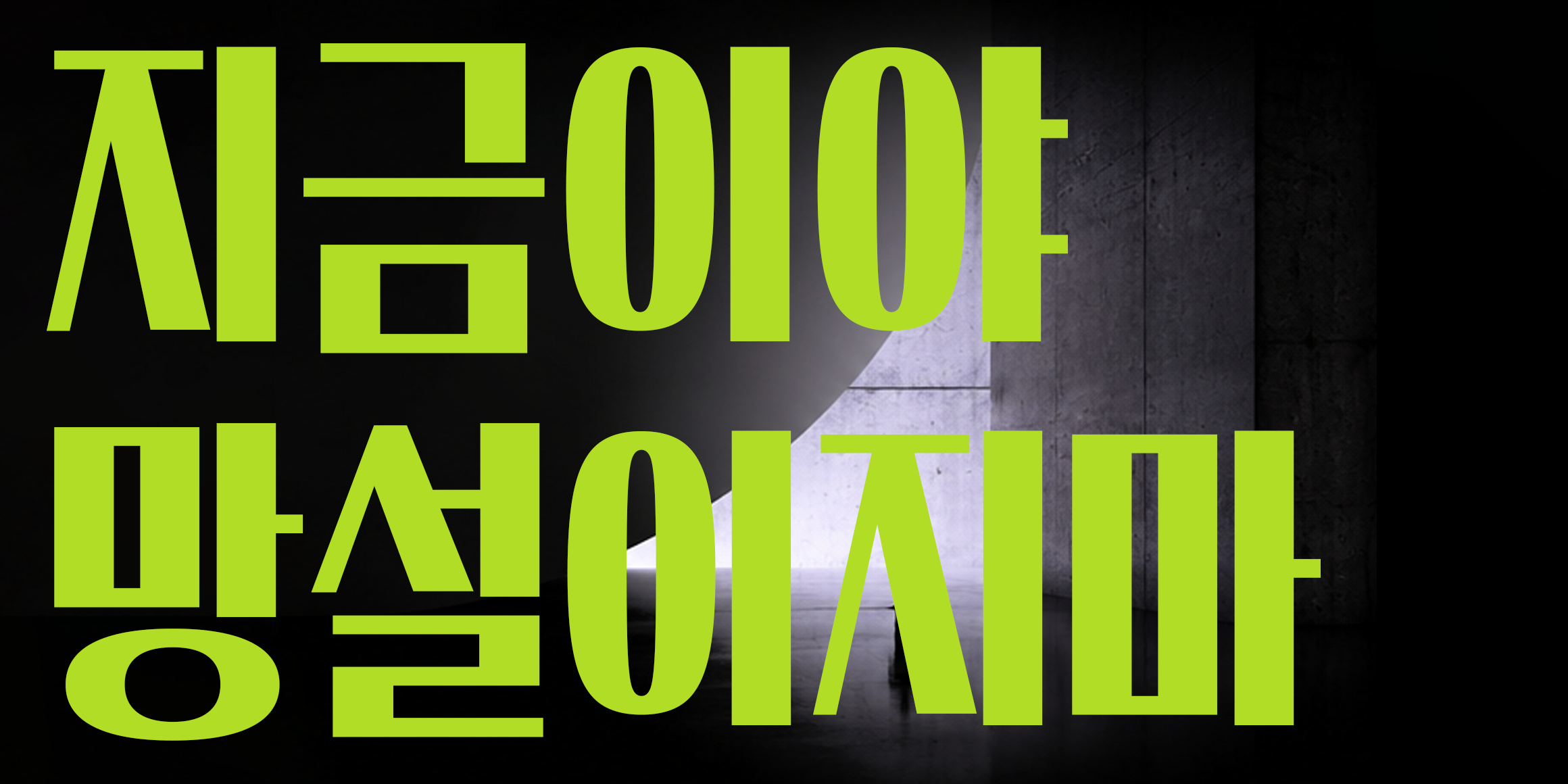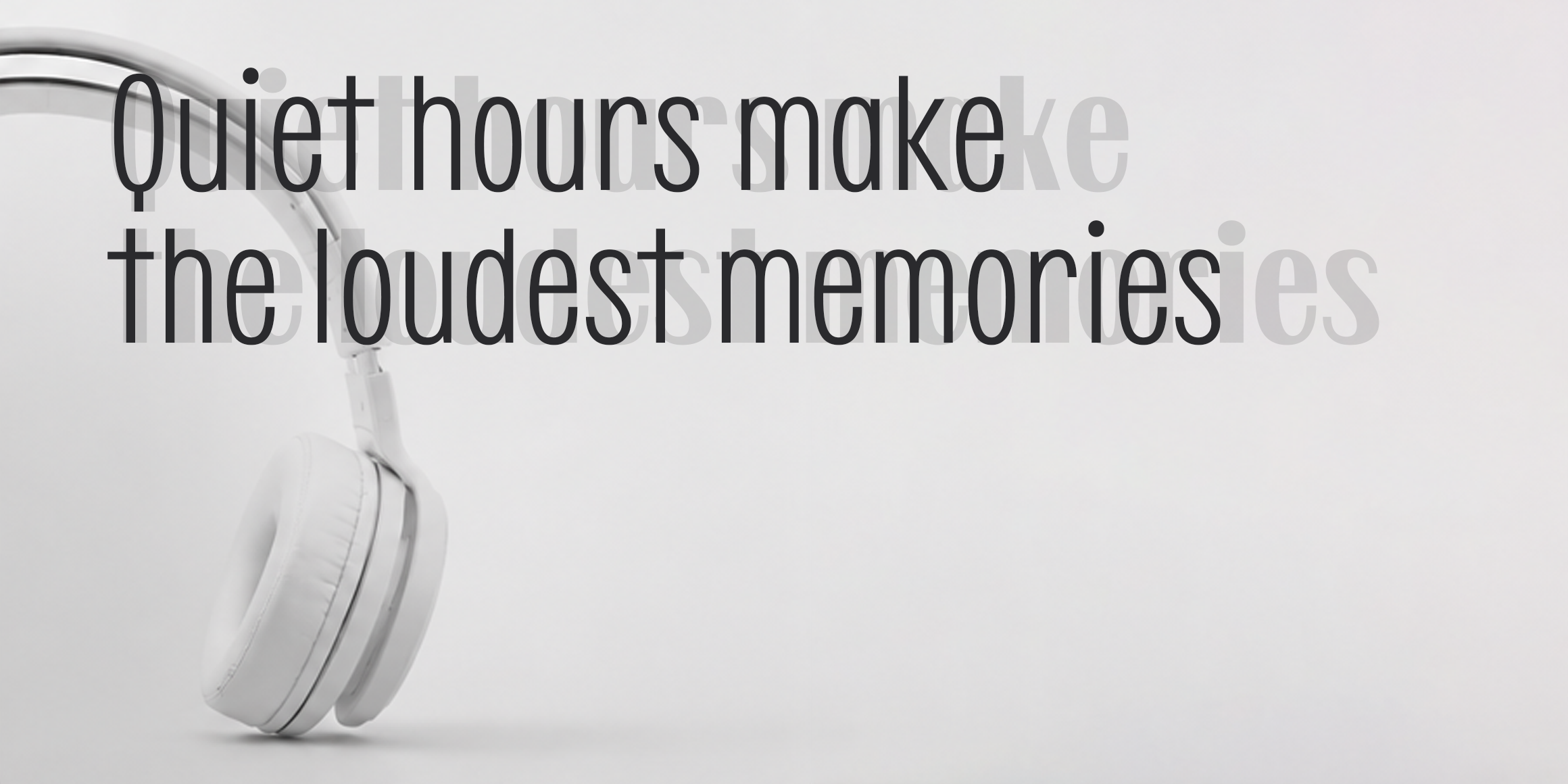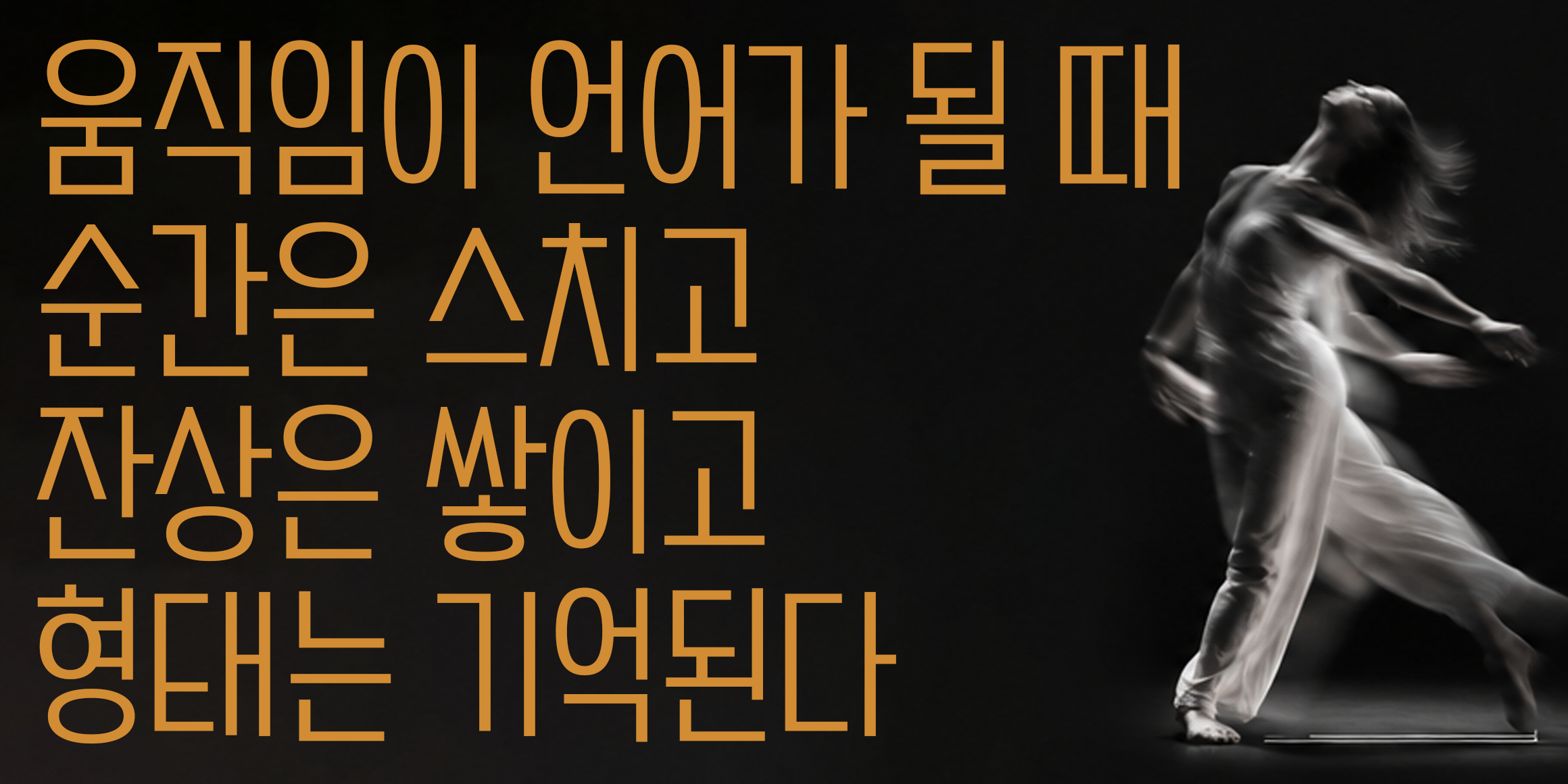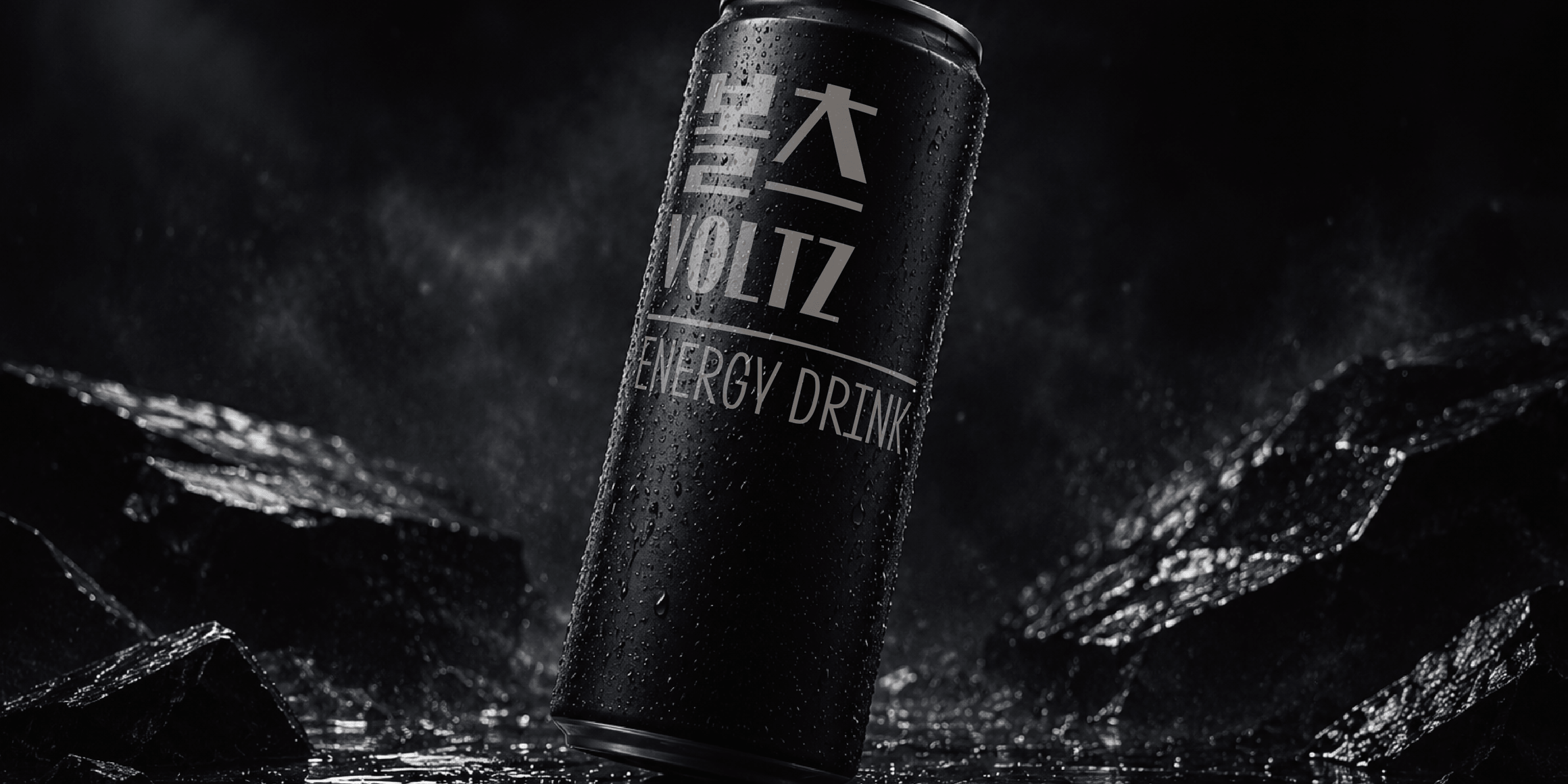
Dain 키다리고딕
Daintype
가로획과 세로획의 두께 비율 변화를 통해 다채로운 패밀리를 구성했습니다. 시각적 무게 중심을 상단에 둔 매력적인 고딕체로, 슬림한 장체 스타일을 적용해 제한된 공간에서도 효율적이고 감각적인 레이아웃을 완성합니다. 뻔하지 않은 개성을 뽐내면서도 산세리프 특유의 탄탄한 기본기를 놓치지 않은 서체입니다.